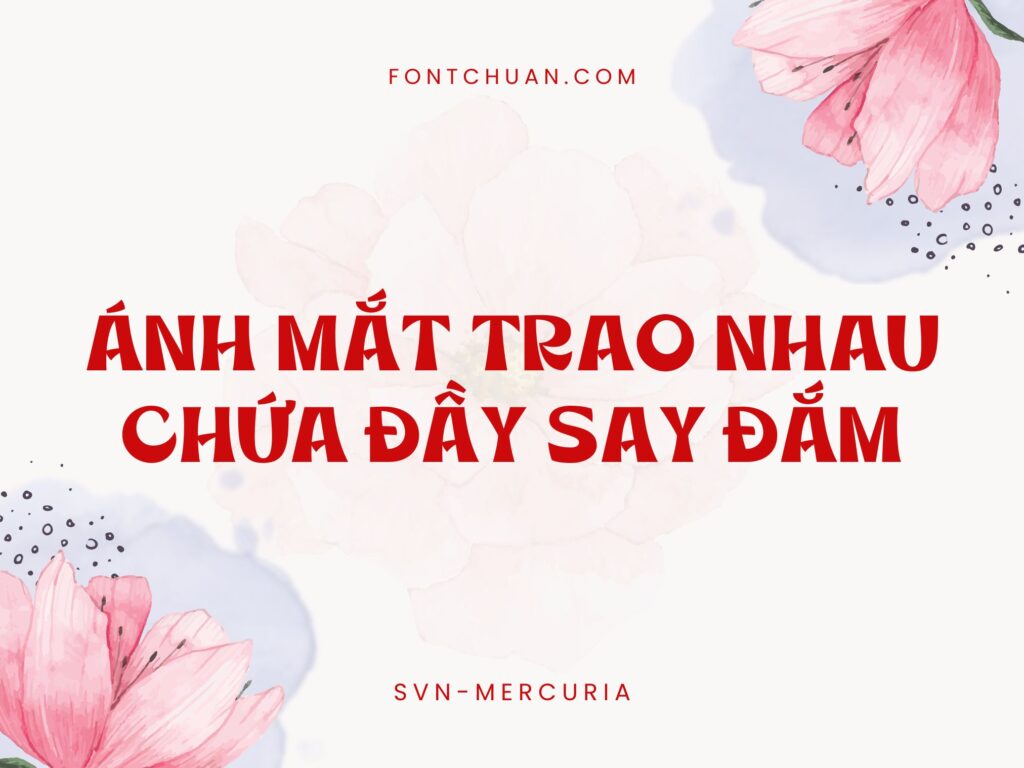
Font SVN Mercuria Việt Hóa
Tác giả Font: Franco Fuentes
Font SVN Mercuria là phiên bản Việt hóa của kiểu chữ Mercuria, được thực hiện bởi STYLEno.1 Fonts. Mercuria là một kiểu chữ đậm, mạnh mẽ và thân thiện, với thiết kế độc đáo cho phép sử dụng trong nhiều ngữ cảnh và dịp khác nhau. Font này bao gồm hơn 240 ký tự, chứa chữ hoa, chữ số, các ký hiệu dấu câu và ký tự đặc biệt khác, hỗ trợ đa ngôn ngữ. Định dạng tệp bao gồm OTF và TTF. Mercuria phù hợp cho nhiều mục đích sử dụng như thiết kế logo, tiêu đề, bao bì sản phẩm và các ấn phẩm truyền thông.
SVN Mercuria lý tưởng cho các dự án thiết kế yêu cầu sự mạnh mẽ và thân thiện, như thiết kế logo, tiêu đề, bao bì sản phẩm và các ấn phẩm truyền thông. Các ngành nghề như quảng cáo, công nghệ và giáo dục có thể tận dụng font này để tạo điểm nhấn trong thiết kế. Ngoài ra, font cũng thích hợp cho các sự kiện như Tết, Valentine, các lễ hội, và đặc biệt có thể sử dụng như một Font chữ Giáng Sinh để trang trí thiệp, poster hay banner mùa lễ hội, mang đến không khí ấm áp, vui tươi và rộn ràng cho các sản phẩm thiết kế.